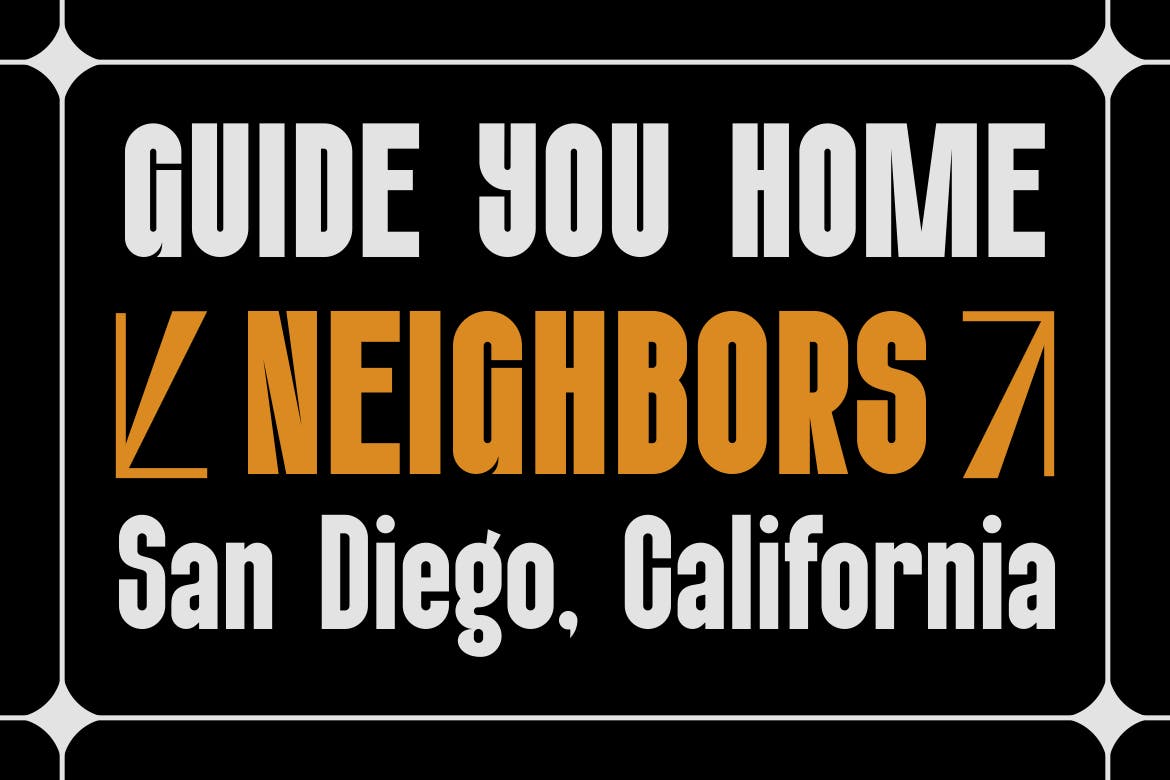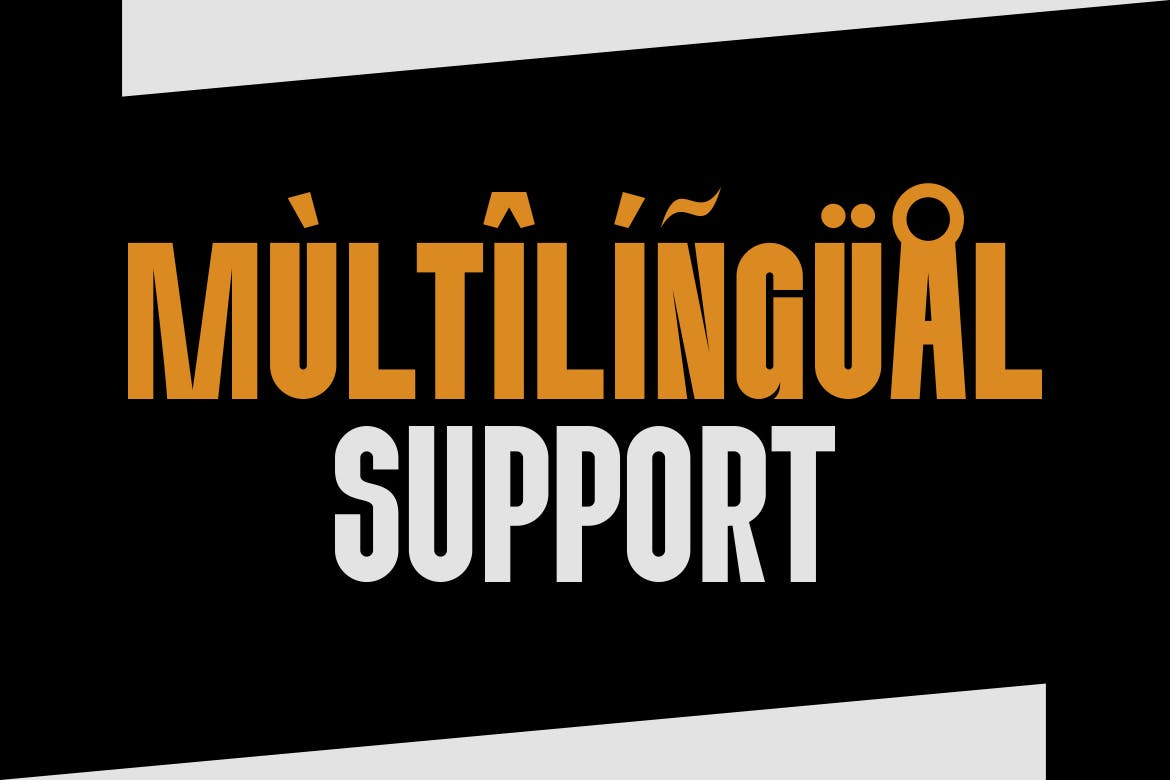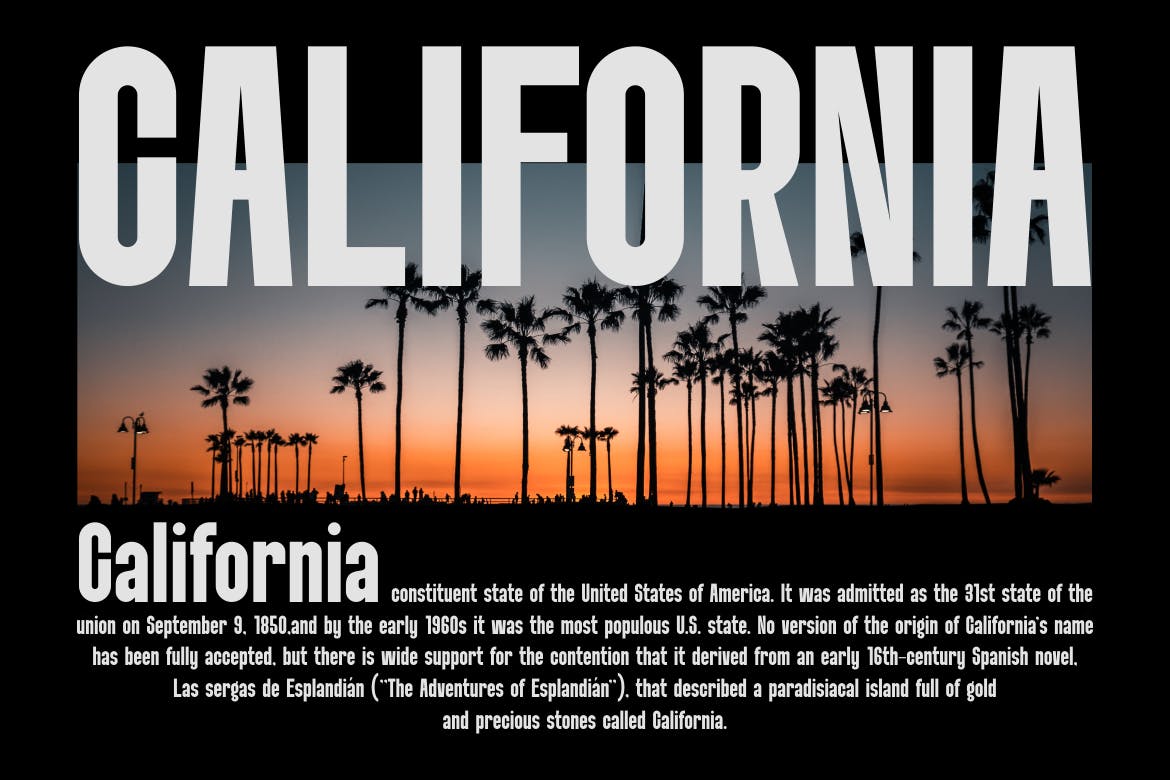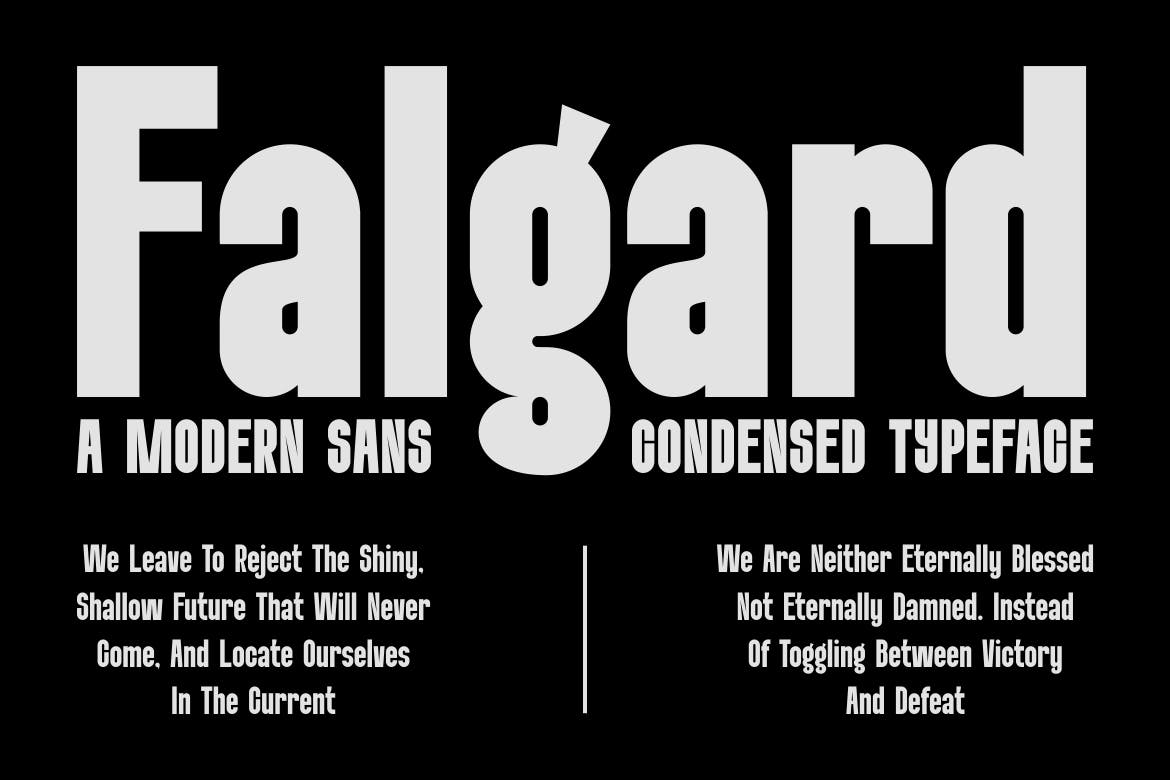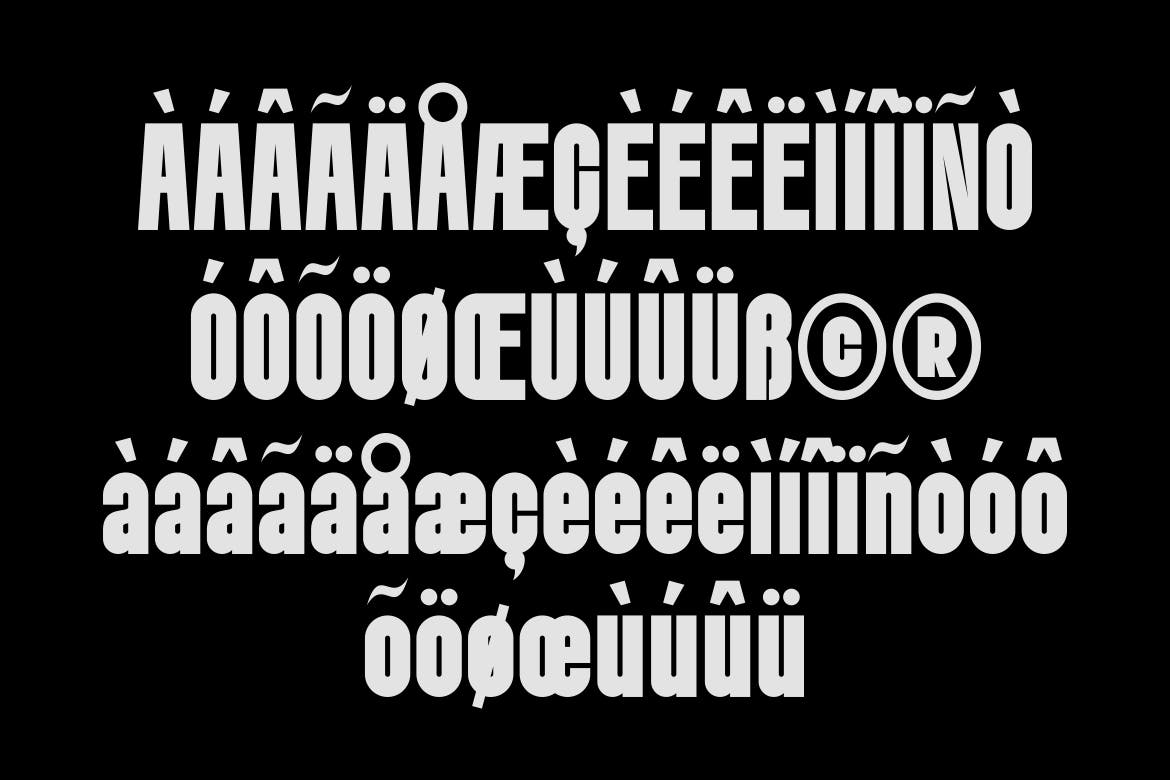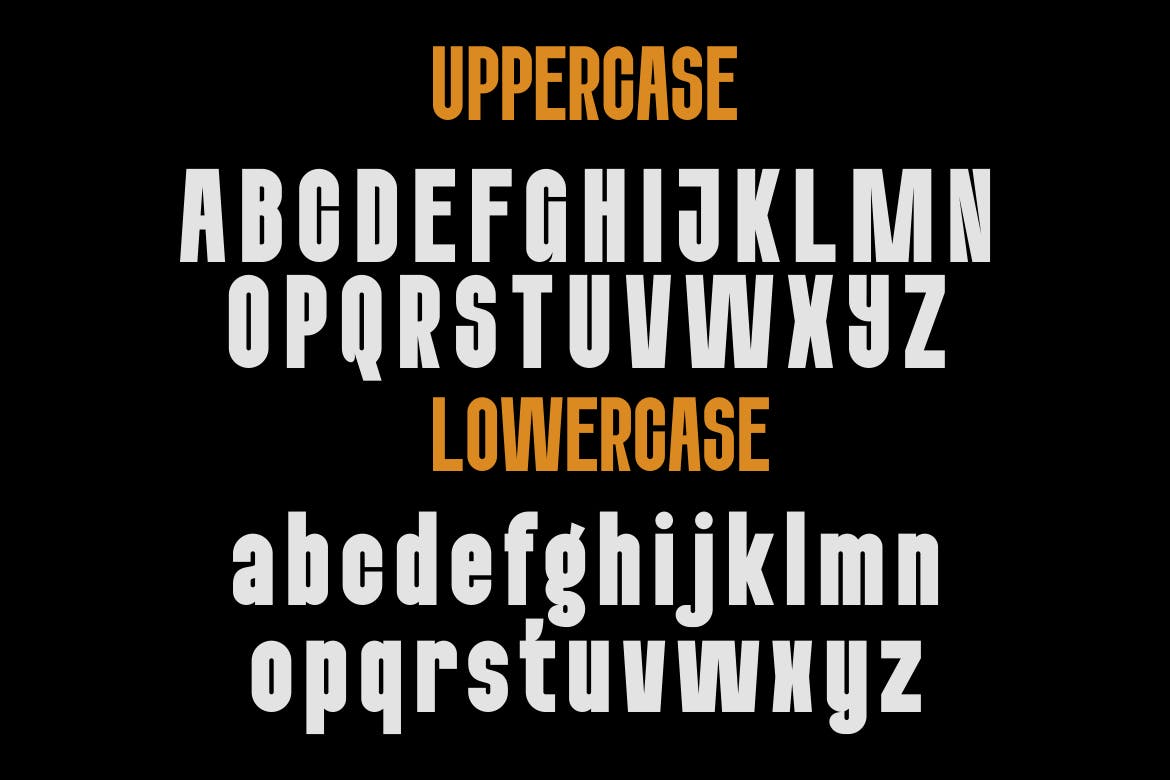
Falgard A Modern Condensed Sans Font
فونت Falgard با طراحی مدرن و منحصر به فرد، گزینه‌ای عالی برای پروژه‌های شماست.
به شما فونت جدید و مدرن Falgard Font را معرفی می‌کنیم. این فونت، یک فونت نمایش برجسته و اصیل است که برای هر پروژه برندینگ مانند لوگو، طراحی قالب، محصولات و بسیاری موارد دیگر مناسب است و در طیف وسیعی از زمینه‌ها برجسته عمل می‌کند.
• حروف بزرگ
• حروف کوچک
• چند زبانه